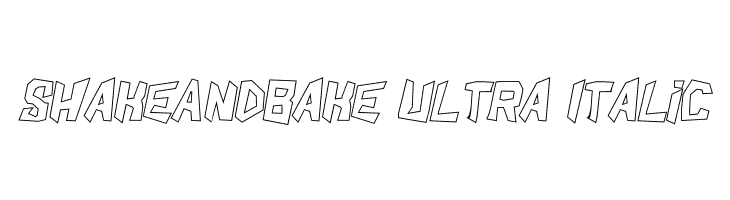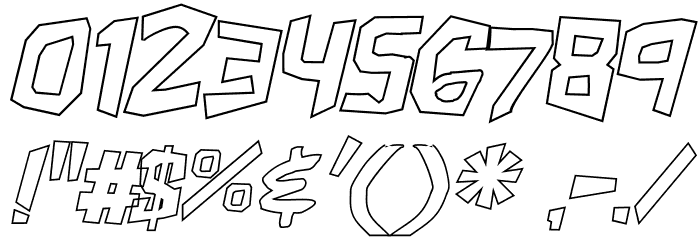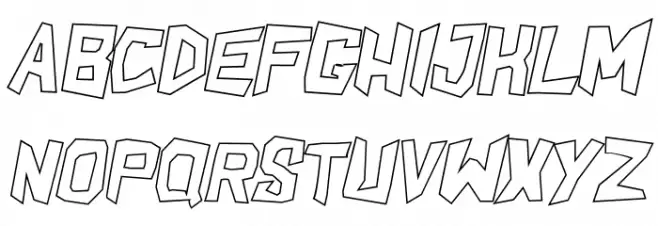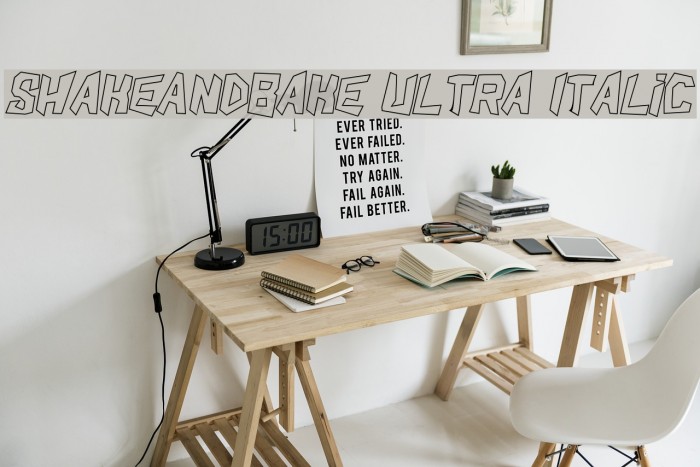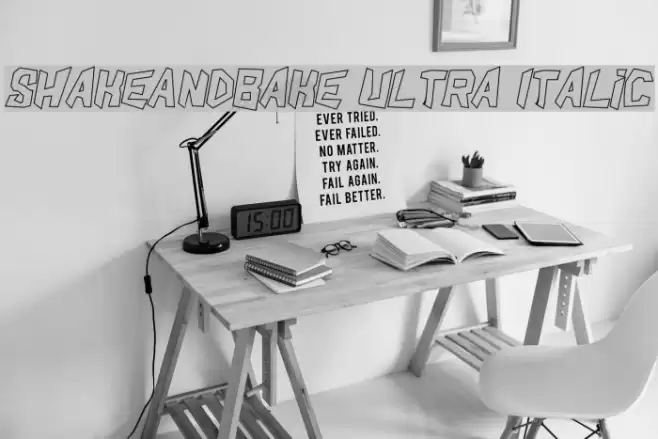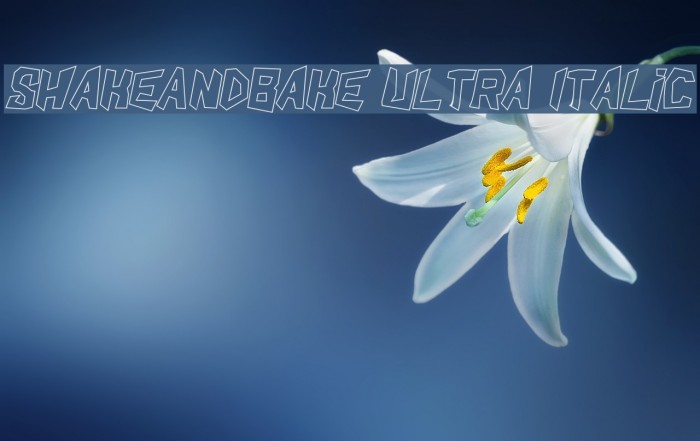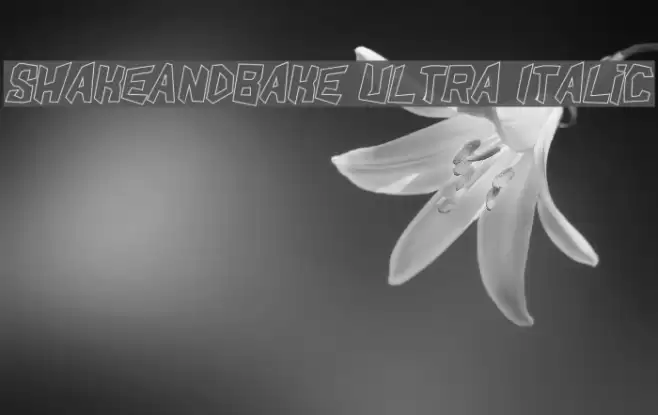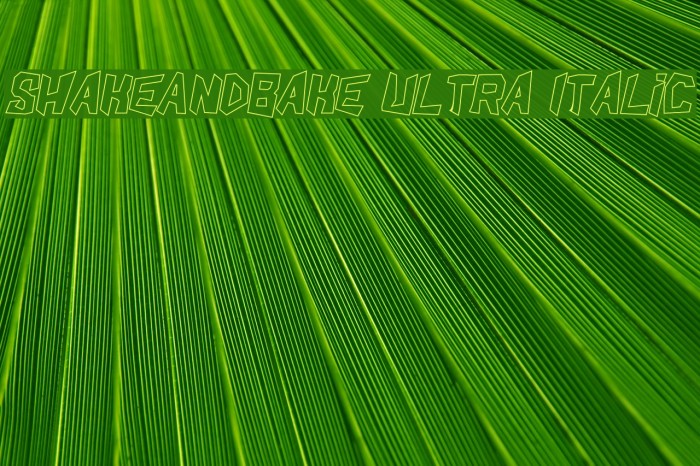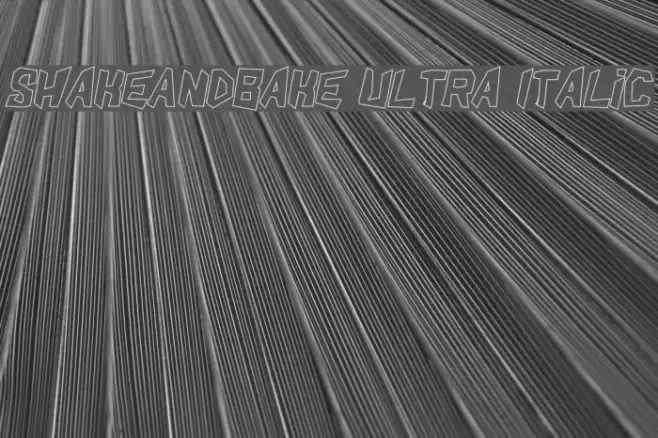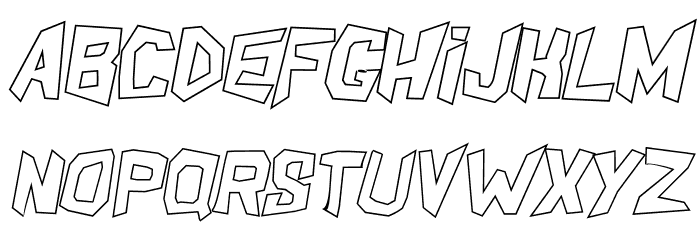
ShakeAndBake Ultra Italic Font
| Vorgeschlagene Projekte | Ideal for posters, logos, and branding materials that need a dynamic and energetic look. |